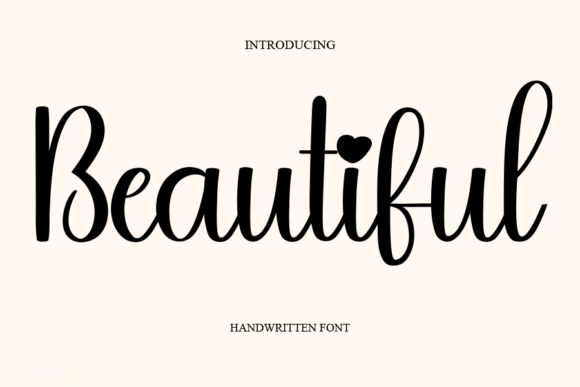
Beautiful
Beautiful : la police manuscrite qui sublime vos créations
Vous cherchez une police simple, élégante et pleine de caractère ? Beautiful répond à toutes ces exigences. Conçue à la main, cette typographie offre un rendu authentique qui apporte fraîcheur et naturel à chaque projet. Que vous travailliez sur des cartes de vœux, des affiches percutantes ou des titres accrocheurs, Beautiful s’adapte avec grâce et polyvalence.
Pourquoi choisir Beautiful ?
- Aspect manuscrit unique : chaque glyphe ressemble à une écriture à la main, ce qui confère une touche personnelle et chaleureuse.
- Polyvalence exceptionnelle : idéale pour les cartes de vœux, les invitations, les logos, les titres de blog et même les bannières publicitaires.
- Lisibilité optimale : les lettres sont soigneusement espacées, garantissant une lecture claire même à petite taille.
Applications concrètes de Beautiful
Imaginez vos prochains projets avec Beautiful :
- Cartes de vœux personnalisées pour les fêtes de fin d’année.
- En-têtes de newsletters qui captent l’attention dès le premier regard.
- Logos de petites entreprises cherchant une identité douce et authentique.
- Affiches événementielles où le texte doit se démarquer sans effort.
- Designs de produits (étiquettes, packaging) pour une touche artisanale.
Conclusion
En résumé, Beautiful est bien plus qu’une simple police : c’est un véritable atout créatif qui donne vie à vos idées. Son style manuscrit, sa lisibilité et sa grande adaptabilité en font le choix parfait pour tous ceux qui souhaitent ajouter une note de fraîcheur et de naturel à leurs projets. N’attendez plus, téléchargez Beautiful dès aujourd’hui et transformez vos créations en œuvres mémorables !